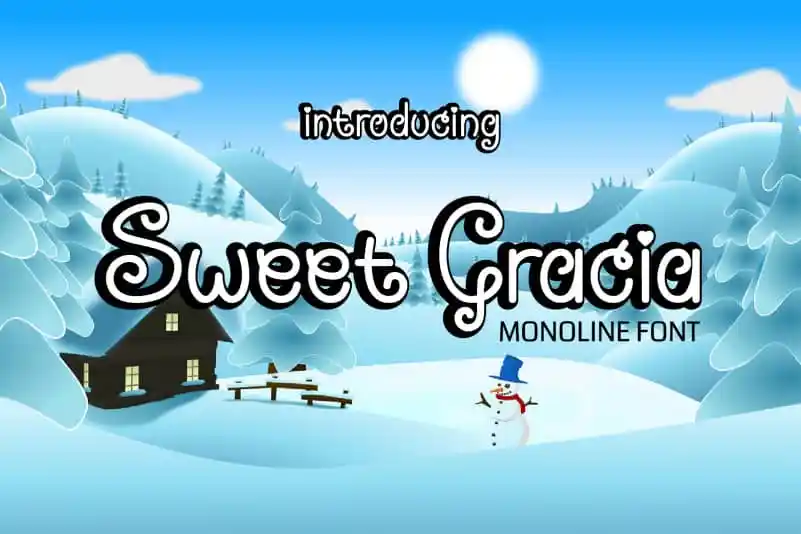
Sweet Gracia – Monoline Font – Download Grátis
A fonte Sweet Gracia – Monoline oferece uma experiência visual atraente para designers gráficos apaixonados. Esta elegante font monolínia é perfeita para projetos de arte criativa, dando um toque moderno e limpo a qualquer design. Seja você um designer de moda ou de decoração, Sweet Gracia – Monoline irá transformar suas ideias em verdadeiros trabalhos de arte. Suas linhas sólidas e retas são projetadas para dar uma aparência minimalista ao seu trabalho final, sem perder a beleza e o contraste necessário para destacar seus designs únicos. A Sweet Gracia – Monoline é um recurso valioso para quem deseja adicionar uma personalidade única e moderna à sua identidade de marca ou arte digital. Jprint Studio criou essa fonte exata, ideal para aqueles que buscam complementar seu trabalho com algo que seja tão sofisticado quanto ele é funcional.